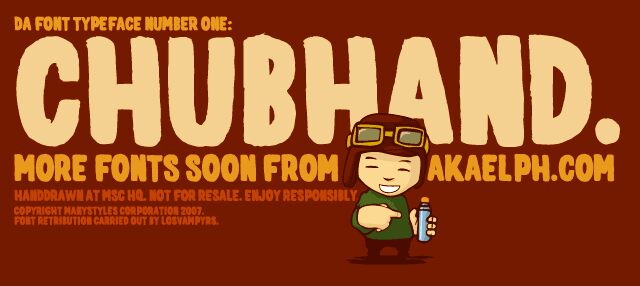
Elph Chubba, eine kostenlose Cartoon-Display-Schrift, wirkt wie handgeschnittene, klobige Großbuchstaben in breiten, abgerundeten Formen. Die Buchstaben wirken eher wuchtig und verspielt als perfekt, mit unebenen Kanten und weichen Ecken, die der gesamten Schrift einen lebendigen, comicartigen Rhythmus verleihen.
Sie passt hervorragend für Plakatüberschriften, Kinderverpackungen, Party-Flyer, Comic-Titel und fröhliche Logos, bei denen eine kostenlose Schrift eine große, markante Silhouette statt glatter Eleganz benötigt. Da die Großbuchstaben so dick und vereinfacht sind, eignet sich Elph Chubba auch gut für kurze Cover-Texte, Titelkarten und Monogramme, die einen freundlichen, leicht tollpatschigen Charakter brauchen.